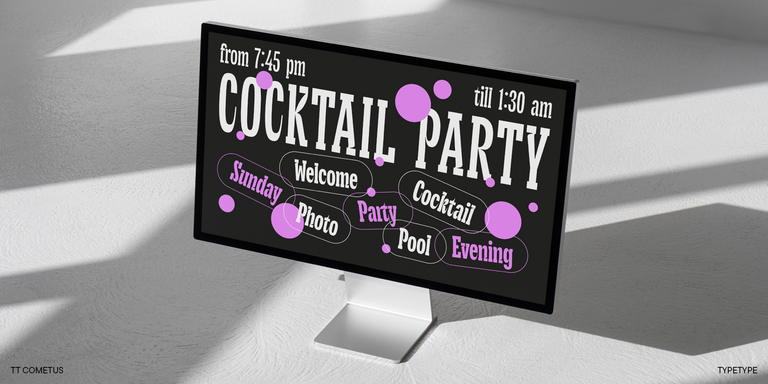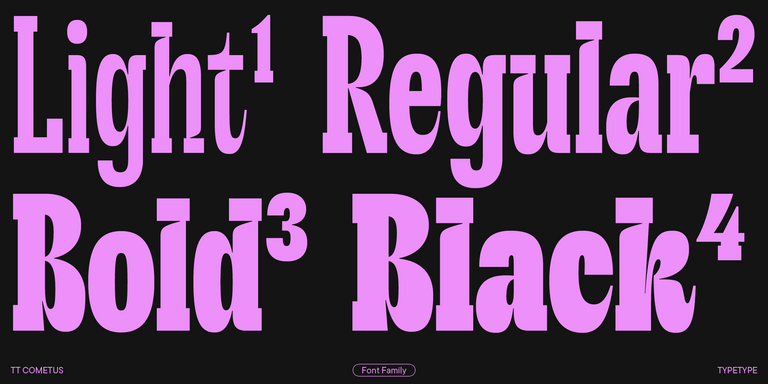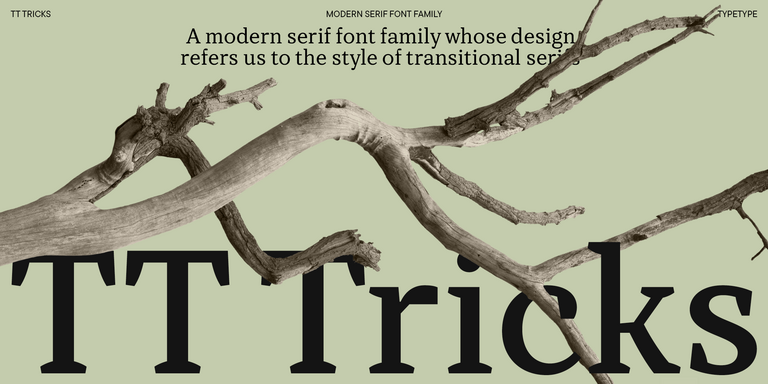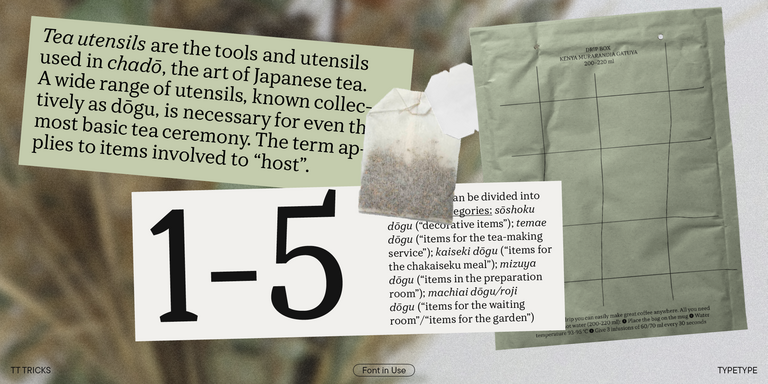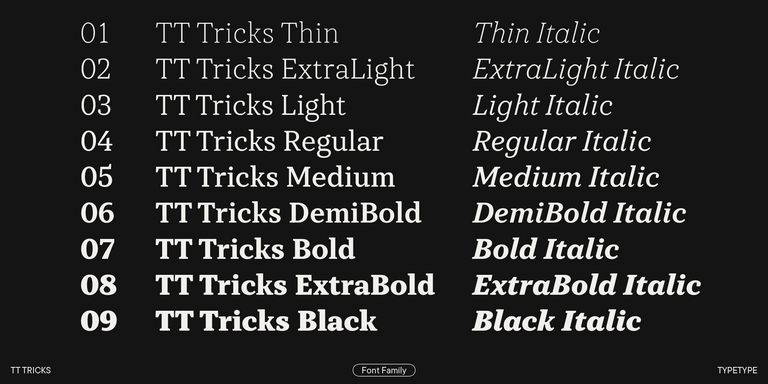
TT Polihaus es una grotesca experimental que, a primera vista, parece normal, pero después se descompone y adquiere una estructura stencil.
TT Nooks Serif es una tipografía serif moderna de exhibición con un ligero toque de egocentrismo. Tiene un carácter definido y firme, pero al mismo tiempo elegante y distinguido.
TT Nooks Script presenta un diseño único que no tiene equivalentes directos.
TT Dott — es una grotesca pixelada experimental en la que el píxel se basa en un círculo. Es una fuente plástica y poco común, de carácter decorativo, que evoca asociaciones tanto con el bordado como con las fiestas techno.
TT Turns es una impactante sans serif geométrica con elementos expresivos. Esta versátil tipografía funciona excepcionalmente bien en textos corridos y, en tamaños grandes, adquiere un marcado carácter display.
TT Regins es una serif moderna escocesa. Su fuerte contraste y sus afiladas serifas triangulares le otorgan un carácter severo y dominante, mientras que las formas refinadas, las minúsculas ampliadas y las proporciones ligeramente condensadas y estáticas aportan elegancia al diseño.
TT FRANTZ ES UNA FUENTE VARIABLE EXPERIMENTAL QUE DESTACA POR SU DELGADEZ Y LIGEREZA. LA VARIACIÓN DE LA FUENTE AFECTA EL CAMBIO EN LA ALTURA DE LA LÍNEA MEDIA: MOVIENDO EL CONTROL DESLIZANTE DEL EJE PUEDES SUBIR O BAJAR FÁCILMENTE LA LÍNEA MEDIA DE LA TIPOGRAFÍA.
TT Quaris es una exquisita sans serif moderna de alto contraste cuyo diseño equilibra suavidad y nitidez. Las formas de los glifos son fluidas y tienden a la redondez, aunque también incorporan elementos afilados.
TT Ricordi Allegria es una grotesca florentina contemporánea, elegante e inteligente.
TT Modernoir es una display sans serif con proporciones dinámicas. Las líneas fluidas y las delicadas formas Art Nouveau se combinan perfectamente con el flujo rítmico y la libertad improvisadora del jazz.
TT Moons es una serif estilizada y contrastada. Esta familia tipográfica funciona especialmente bien en diseños de estilo clásico. TT Moons pertenece al estilo de las tipografías modernas glyptal.
TT Ricordi Greto es un proyecto experimental inspirado en una placa de suelo fechada en 1423 encontrada en la Basílica de Santa Croce de Florencia.
TT Norms® Pro es una leyenda tipográfica adoptada por marcas de renombre mundial. Evolucionada a través de múltiples iteraciones, ha conquistado MyFonts y redefinido la versatilidad tipográfica. Un caballo de batalla del diseño que pasa de ser una herramienta discreta a un aliado creativo imprescindible.
TT Commons™ Pro es la joya tipográfica del estudio. Una fuente tan versátil que desafía toda categorización, uniendo estilo y funcionalidad sin esfuerzo. Para los diseñadores que buscan una base universal que eleve cada proyecto, esta es la elección definitiva.
TT Hoves Pro es una sans serif escandinava que susurra elegancia minimalista. A la vez discreta y distintiva, es el arma secreta del diseñador, capaz de convertir desafíos complejos en poesía visual con una precisión sin esfuerzo.
TT Supermolot Neue revoluciona la comunicación visual. Esta sans serif modular y avanzada capta el pulso de la innovación tecnológica, aportando una visión electrizante a todo, desde interfaces de videojuegos inmersivos hasta narrativas visuales contundentes.
TT Firs Neue es una sans serif equilibrada impregnada de la filosofía del diseño escandinavo. Elegante y versátil, fue perfeccionada a través de dos revisiones deliberadas hasta alcanzar la perfección tipográfica.
TT Rounds Neue es una fuente suave y amigable que sabe cómo destacar. En sus estilos más ligeros se presenta minimalista y neutral. En sus estilos más audaces se expande y alcanza la máxima redondez, irradiando un encanto infantil.
TT Fors es una navaja suiza del diseño tipográfico. Esta sans serif geométrica ofrece una versatilidad absoluta gracias a sus proporciones limpias y refinadas. Puede utilizarse tanto para definir interfaces como para crear acentos visuales.
TT Ramillas es una fuente con serifas elegante y contemporánea que eleva el diseño a la categoría de arte. Caracterizada por sus estilos decorativos únicos y capitulares con ornamentos florales, crea experiencias visuales realmente únicas. Ya presente en más de 3000 sitios web en todo el mundo, ha sido galardonada con el premio Modern Cyrillic y redefine la sofisticación tipográfica.
TT Cometus es una tipografía expresiva que cautiva desde el primer instante.
TT Travels Next es una moderna y muy actual sans serif display de gran anchura, diseñada para utilizarse tanto en medios impresos como digitales.
TT Globs es la primera tipografía de la línea TypeType Starter Kit.
TT Ricks es una extravagante serif de estilo elzeviriano para la que palabras como “tierna” o “tranquila” definitivamente no son adecuadas.